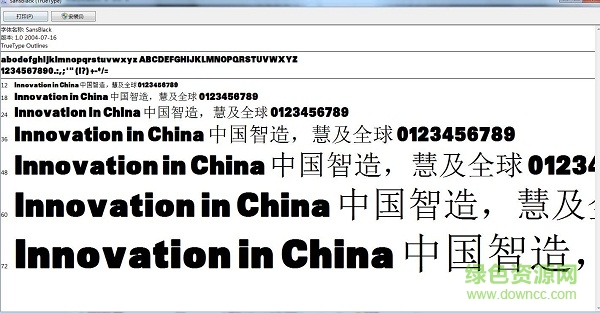
sansblack字體是一款十分醒目的無(wú)襯線字體,線條粗結(jié)構(gòu)寬,端正大方,設(shè)計(jì)獨(dú)到,有著鮮明的視覺(jué)沖擊力,多為標(biāo)題使用,需要就來(lái)綠色資源網(wǎng)下載體驗(yàn)吧!
【變換結(jié)構(gòu)】
結(jié)構(gòu)是字體構(gòu)成的法則,以什么法則來(lái)組建字體,在字體構(gòu)成中以什么形成字體的個(gè)性特色,這都要靠結(jié)構(gòu)來(lái)解決,通過(guò)創(chuàng)意性的變化和轉(zhuǎn)換創(chuàng)造出各種新的結(jié)構(gòu)是體現(xiàn)字體創(chuàng)意表現(xiàn)的主要手法!
【結(jié)構(gòu)的再設(shè)計(jì)】
結(jié)體的再設(shè)計(jì),是在傳統(tǒng)字體結(jié)構(gòu)基礎(chǔ)上,有所突破地打破原有字體結(jié)體規(guī)范,根據(jù)視覺(jué)形象的新型審美觀,將某些偏旁部手突破原有結(jié)構(gòu)的構(gòu)成規(guī)律,在原有的結(jié)構(gòu)編排上開(kāi)創(chuàng)出新型的結(jié)構(gòu)。
【突破字體的外形】
在遵循字體總體外形規(guī)范的基礎(chǔ)上,可有所選擇地將其中一到兩個(gè)筆畫突破外形的界定,或向外延伸、相連,或收縮、與其它筆畫相依,其次還可根據(jù)具體表現(xiàn)主題的需要將字體變化成各種無(wú)機(jī)形態(tài)